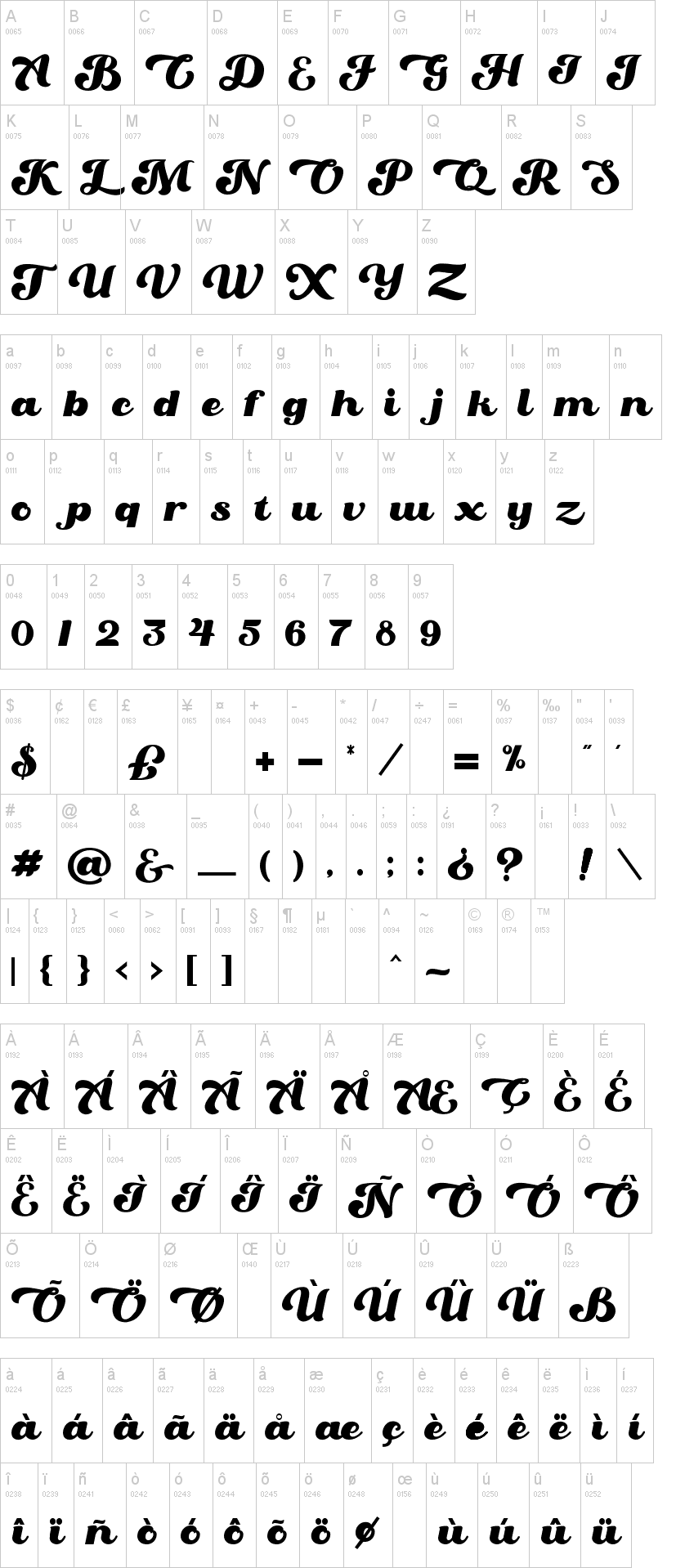
Oaklash是一款具有独特魅力的手写字体,它具有时尚而又具有活力的特点。它的字体特征是精致的笔画,柔和的曲线,以及清晰的细节。它的字体非常容易读取,可以用于各种不同的印刷品,如书籍,海报,标志等。它可以帮助您创造出独特而让人印象深刻的设计,以及更加有趣的文字排版,是一款非常实用的字体。内容介绍
Oaklash是一款非常不错的手写艺术字体,具有很好的视觉感,适合于文化类的宣传设计、商业类品牌的广告和产品包装设计以及个性化文字排版等较多场景。